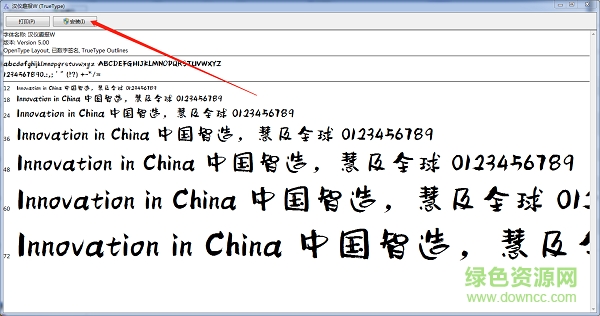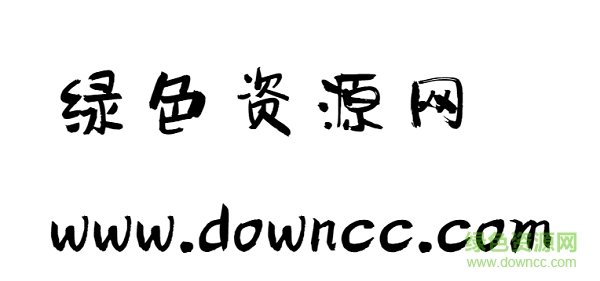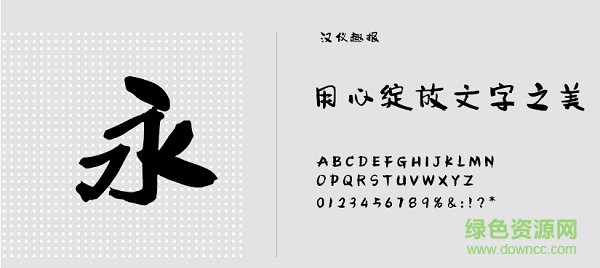
漢儀趣報(bào)w體
漢儀趣報(bào)體是一款極具創(chuàng)意的全新字體,該字體筆畫較粗,類似于筆刷構(gòu)成,簡(jiǎn)短的字體結(jié)構(gòu)看起來簡(jiǎn)單干凈,用戶使用起來也別有一番光景,使用面也極廣,需要的用戶快來綠色資源網(wǎng)下載吧!
漢儀趣報(bào)w字體簡(jiǎn)介:
漢儀趣報(bào)w是漢儀字庫(kù)全新開發(fā)的一款用于設(shè)計(jì)方面的創(chuàng)意字體,該字體線條粗壯有力,給人很強(qiáng)的視覺沖擊力,適用于表達(dá)堅(jiān)實(shí)、略帶古意的標(biāo)題,也可以應(yīng)用于文本裝潢、信息展示、網(wǎng)頁(yè)設(shè)計(jì)、篆刻制模、數(shù)據(jù)制作、裝潢設(shè)計(jì)、計(jì)算藝術(shù)設(shè)計(jì)、視覺設(shè)計(jì)、字帖等一切合法應(yīng)用場(chǎng)景,有喜歡的朋友可免費(fèi)下載收藏!
漢儀趣報(bào)w體預(yù)覽:
漢儀趣報(bào)w